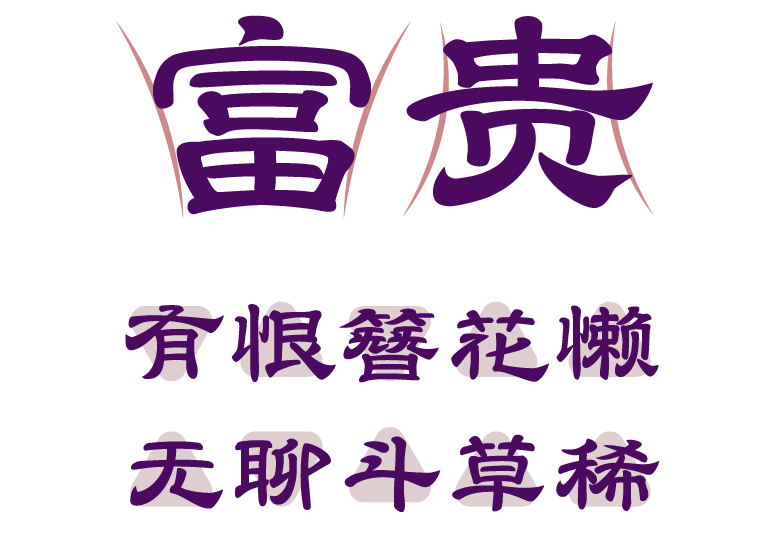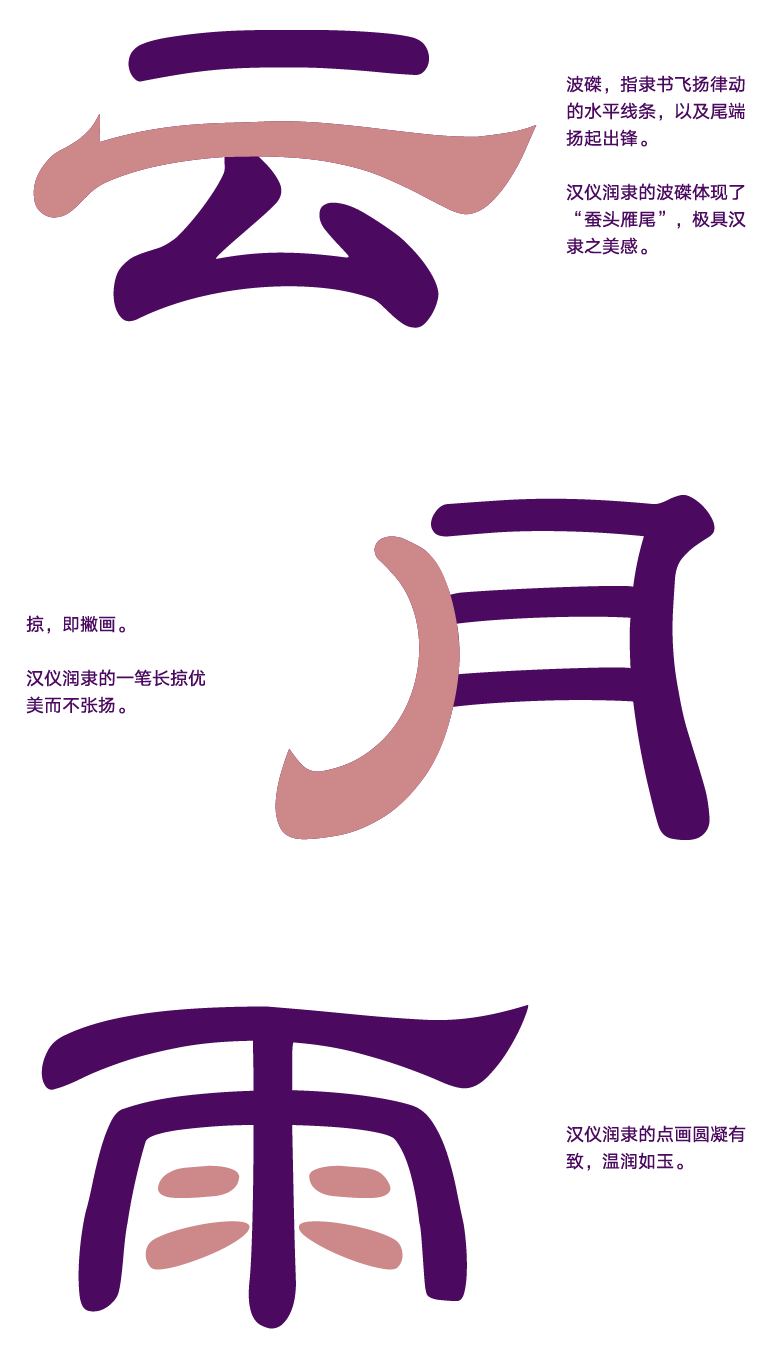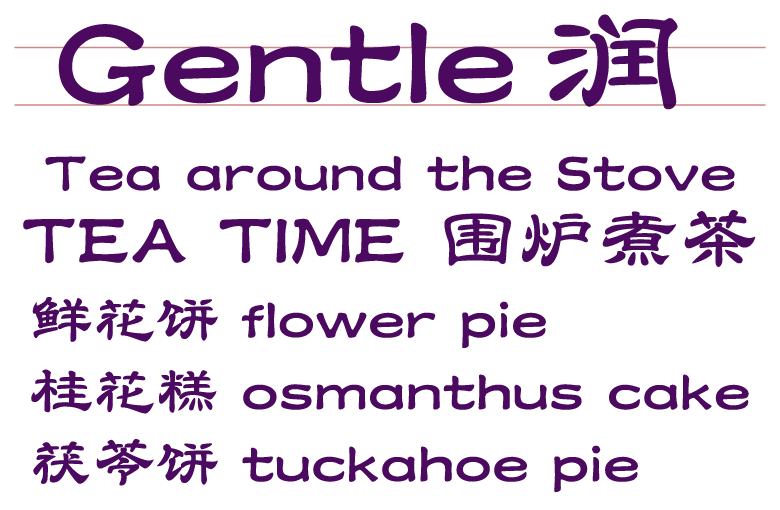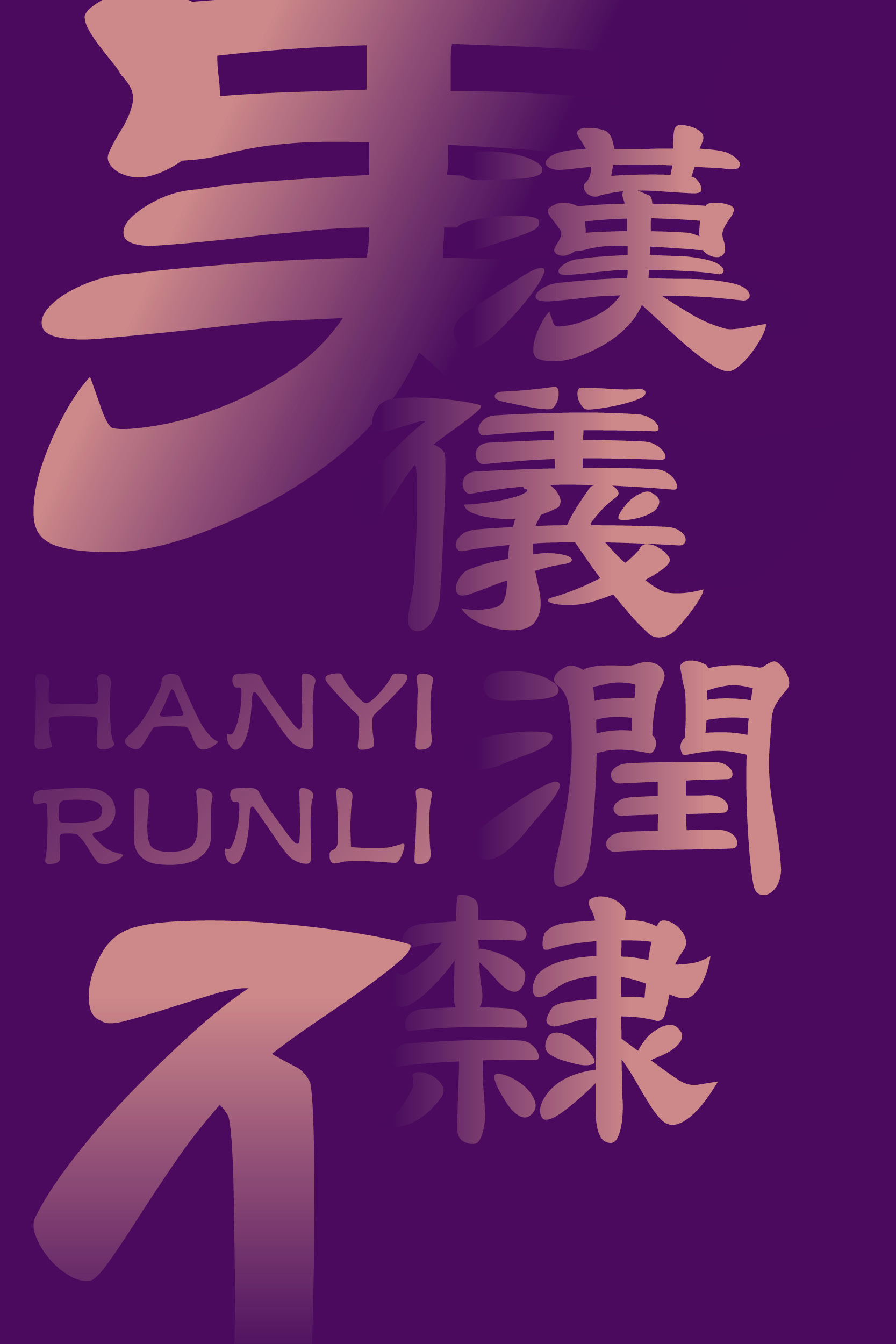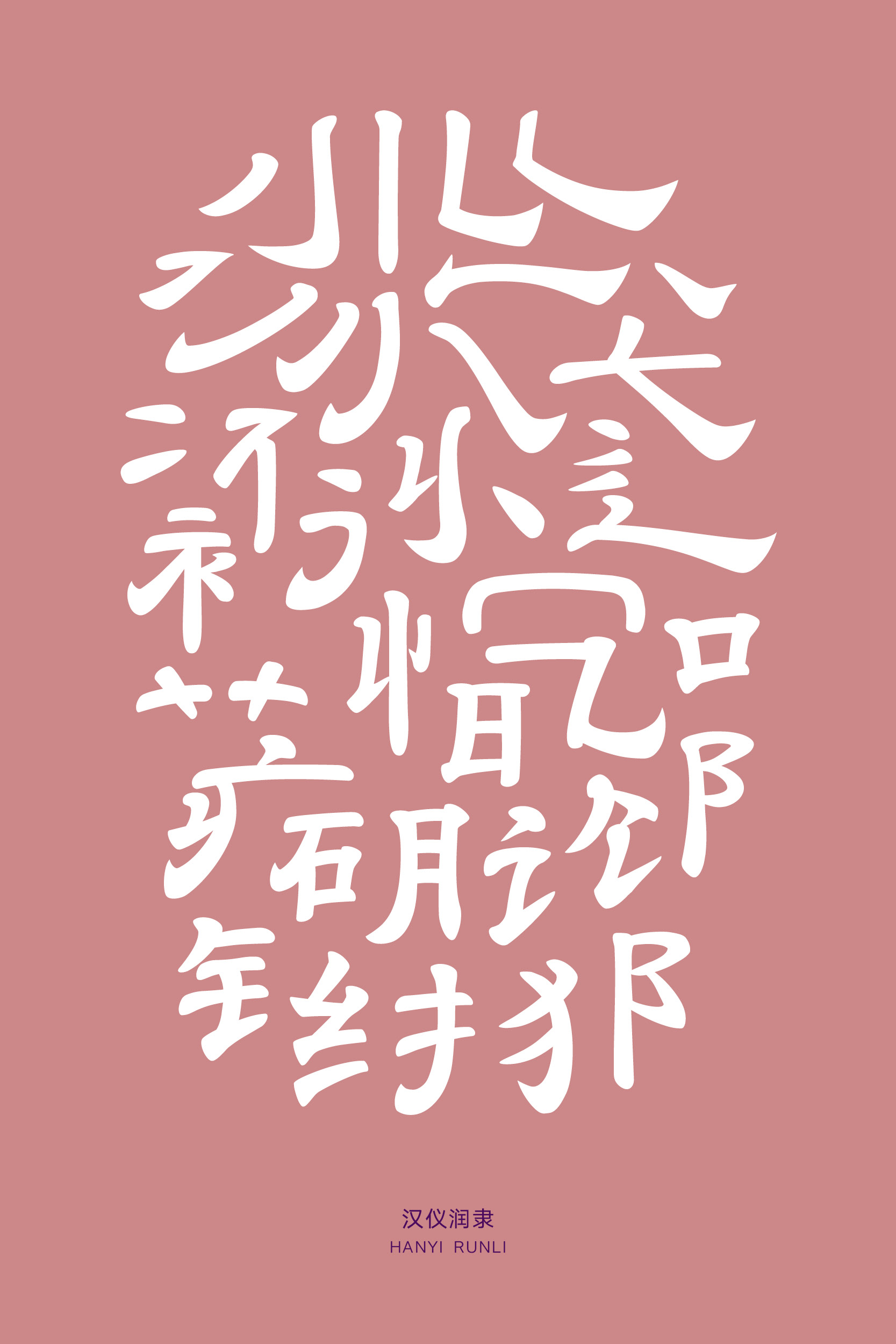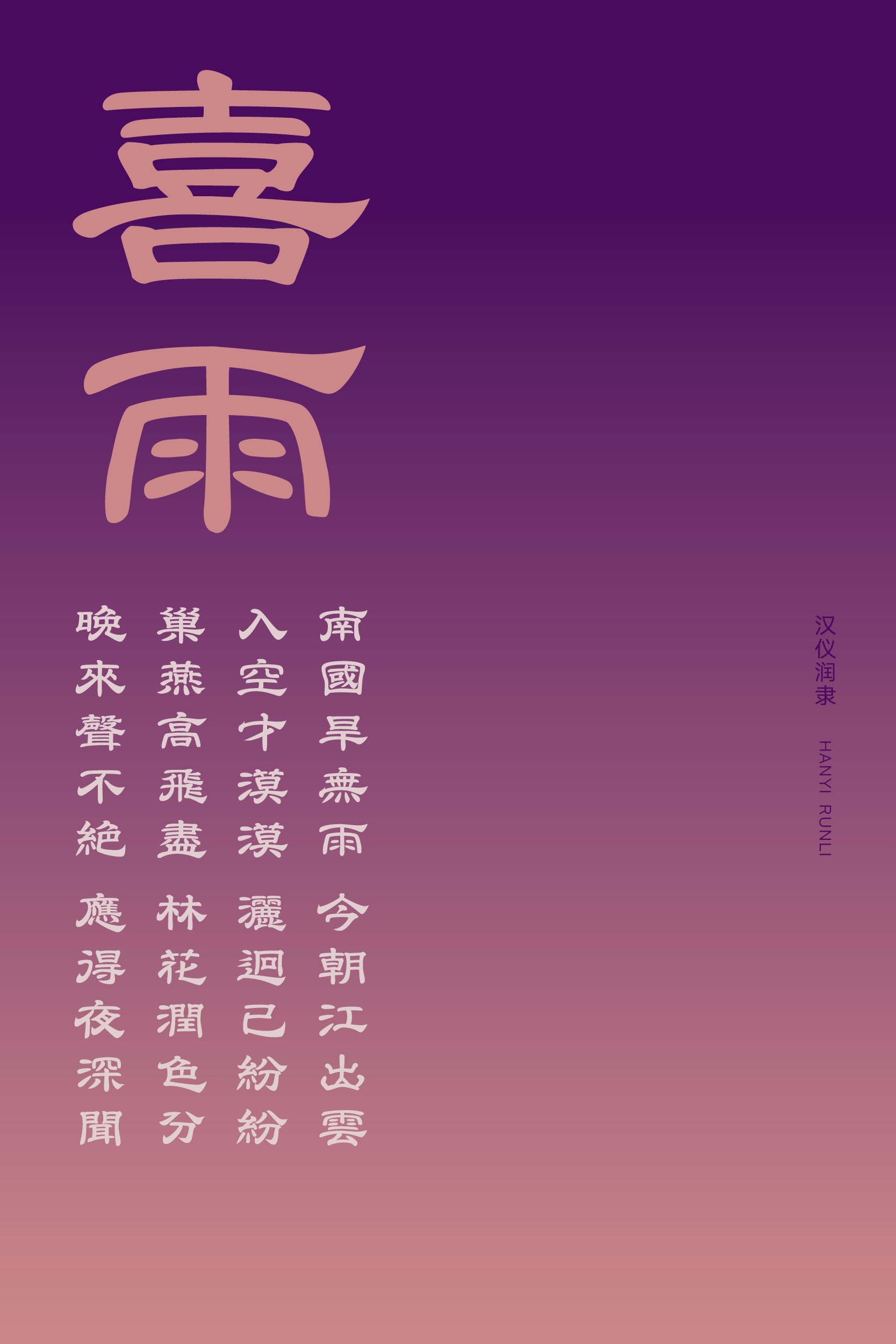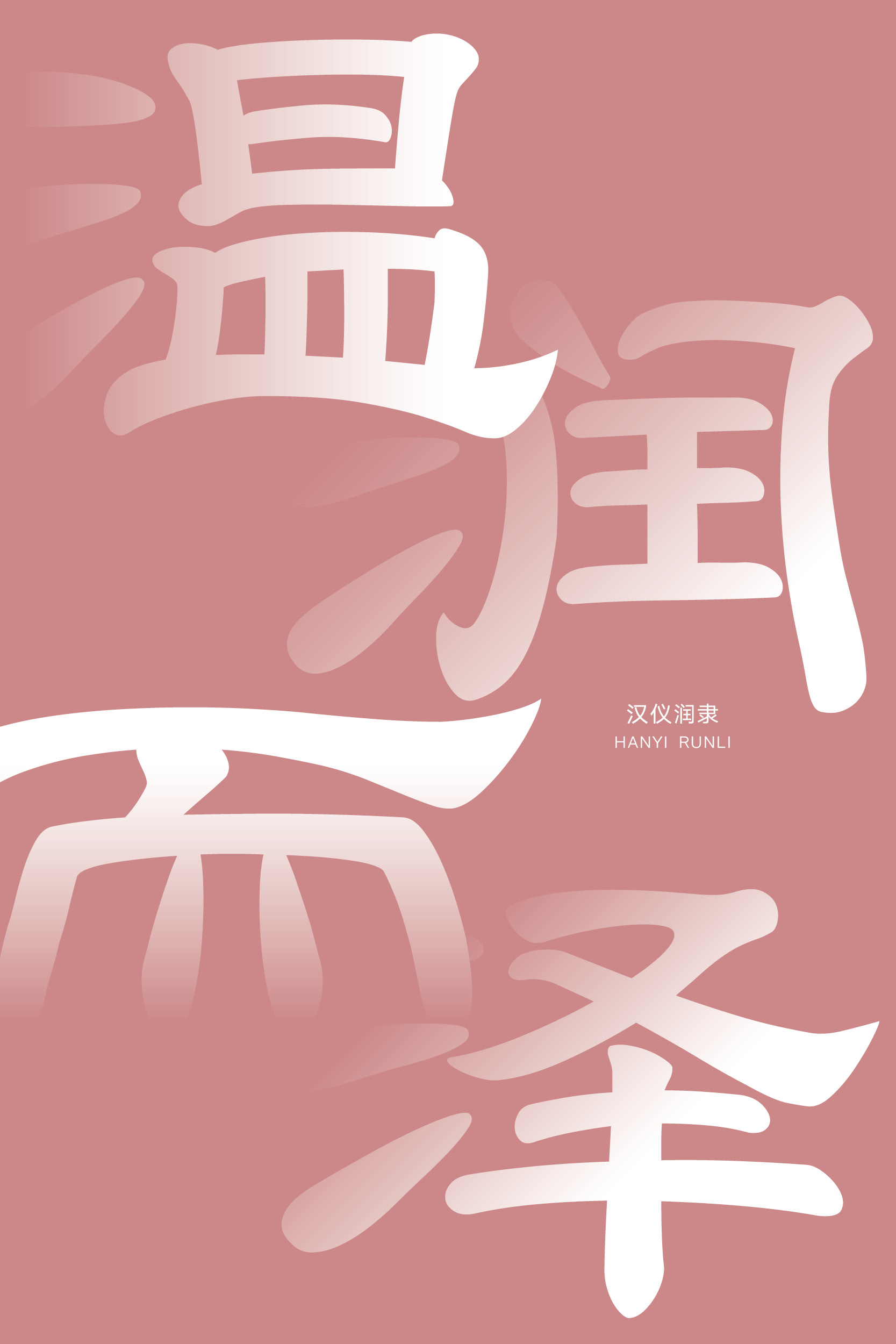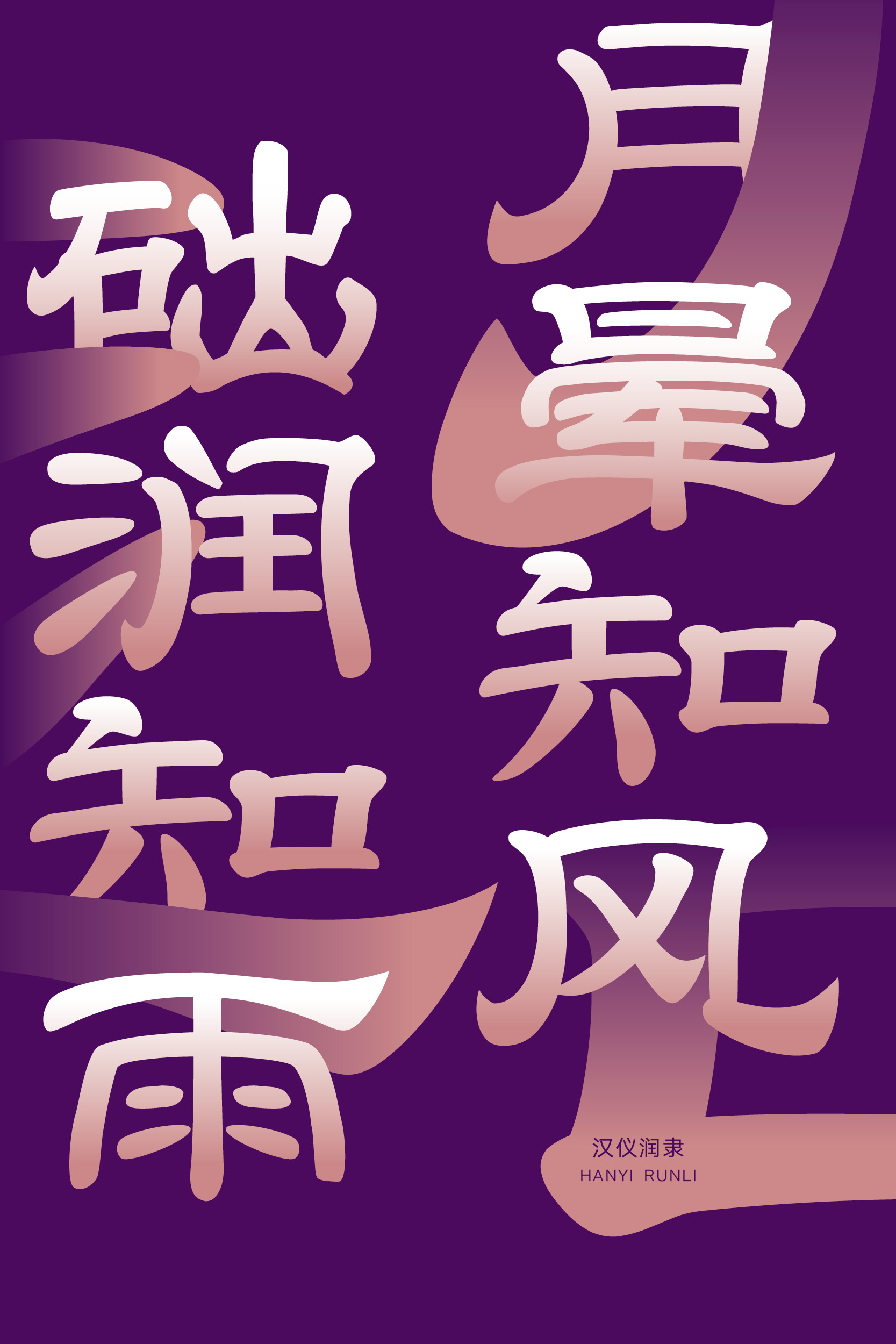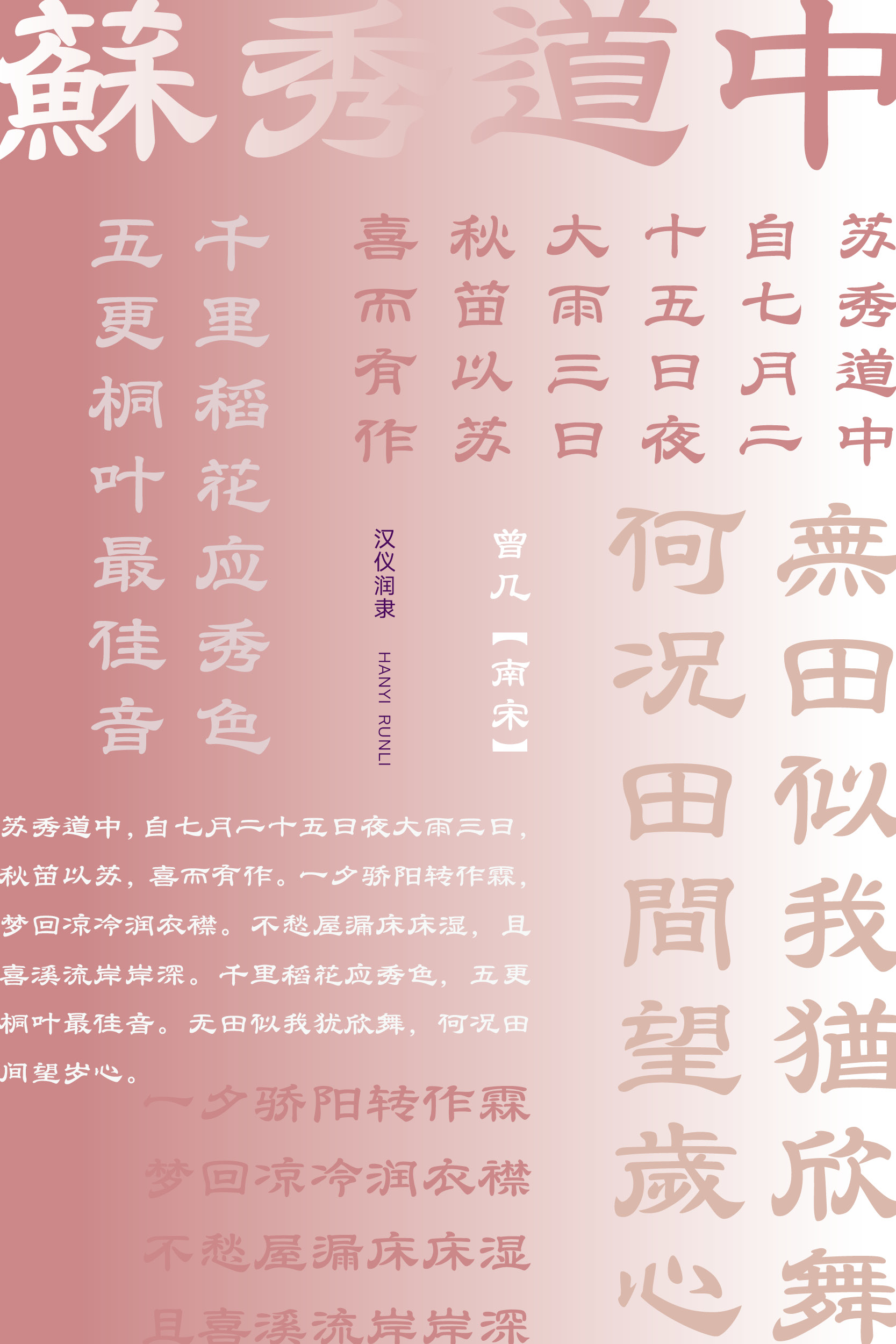
雍容华美,温润雅致的创意隶书
书写字体
汉仪润隶是字由港工作室创作的一款温润雅致的创意隶书书法字体。这款字体字形扁方,结构上紧下松、上松下紧皆有,排版富有意趣。部分结构和笔画引用古代隶书写法,增添了几分古韵。笔画设计莹润丰腴,内敛笔画圆凝,外张笔画谦和。行笔遒劲而蕴动态。汉仪润隶的整体风格雍容华美,适合用于妆饰、茶点、文房等多种场景下较短文案的排版,以渲染典雅浓重的传统文化氛围。
汉仪润隶字形扁方,重心平稳,中宫宽而饱满。
结构依字形或上紧下松、或上松下紧,排版之中富于变化。
笔画设计莹润丰腴,内敛笔画克制而圆凝,外张笔画飘扬而谦和,富有张力。
汉仪润隶强调波磔、长掠,优美又不过分突出,展现了隶书“蚕头雁尾”的特征。点画形态温润如玉。
部分结构和笔画引用古代隶书写法,增添了几分古韵。
汉仪润隶的西文部分同样取横向舒张之势,字形扁方,笔画圆凝润泽,体势平正。